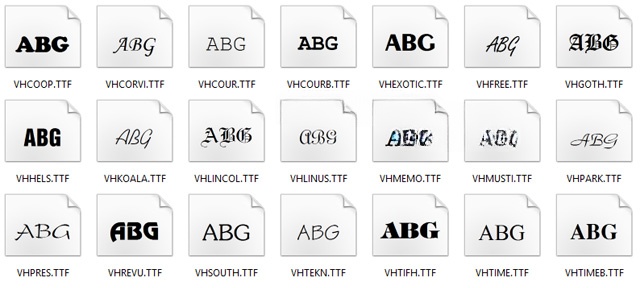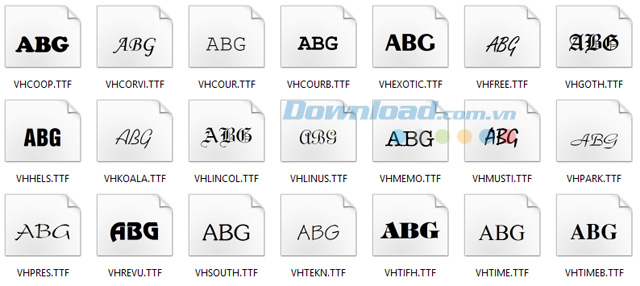
Bộ Font TCVN3 đầy đủFont hỗ trợ Tiếng Việt .Vn
Đây là danh sách bộ font TCVN3 đầy đủ (font tiêu chuẩn Việt Nam 3) hay có tên khác là font ABC bao gồm những font chữ thông dụng như .VNTime, .VNArial...
Bộ Font TCVN3 đầy đủ là font chữ tiếng Việt tiêu chuẩn Việt Nam phổ biến nhất hiện nay với với font chữ cơ bản như: .VNTime, .VNArial, vv. Bộ Font TCVN3 đầy đủ sẽ giúp bạn có thể nhập tiếng Việt khi soạn thảo văn bản, thiết kế, trò chuyện trên các ứng dụng chat và bộ font TCVN3 tương thích với bộ gõ tiếng Việt: Unikey, Vietkey, vv.
Một số font chữ họ TCVN3 trong bộ font TCVN3
Đặc điểm nổi bật của bộ font TCVN3
- Hỗ trợ Tiếng Việt đầy đủ (dấu và ký tự): Font TCVN3 được thiết kế với các mã hóa đặc biệt, giúp hiển thị đầy đủ và chính xác các ký tự tiếng Việt có dấu (sắc, huyền, hỏi, ngã, nặng) và các nguyên âm đặc biệt (.VnTime, .VnArial, v.v.).
- Đa dạng về kiểu chữ: Bộ font này thường bao gồm một hệ thống phong phú với hơn 100 kiểu chữ khác nhau, cho phép người dùng có nhiều lựa chọn về kiểu dáng để làm đẹp văn bản và thiết kế.
- Tương thích cao với bộ gõ: TCVN3 có khả năng tương thích tốt với các bộ gõ tiếng Việt nổi tiếng như Unikey và Vietkey, giúp việc soạn thảo văn bản tiếng Việt trở nên dễ dàng và nhanh chóng (thao tác chọn bảng mã TCVN3 trong Unikey chỉ bằng một cú nhấp chuột).
- Quan trọng cho tài liệu cũ: Rất nhiều tài liệu, văn bản, và sách giáo khoa được soạn thảo từ nhiều năm trước vẫn sử dụng bảng mã TCVN3. Việc cài đặt bộ font này là rất cần thiết để đọc được nội dung của các tài liệu "cũ" này mà không bị lỗi font nghiêm trọng.
Sử dụng TCVN3 sẽ mang lại cho bạn những cảm xúc rất đặc biệt, vì cách soạn thảo sẽ không giống như khi bạn gõ chữ với Unicode. Gõ "lò dùng sóng" sẽ thành "lũ dựng súng", "lè nhè" → "lố nhố", "lâng bâng" → "lõng bõng", "tê mê" → "tờ mờ". Vì là tiêu chuẩn cũ, nên ta thường bắt gặp chuẩn này trong những tài liệu tương đối "cổ". Dù hiện tại, ít người sử dụng chuẩn này, nhưng vẫn sẽ cần đến nó để đọc được các tài liệu hoặc sử dụng trong những yêu cầu đặc biệt.
Bên cạnh đó, với tính năng tương thích cao với nhiều phần mềm và hệ điều hành cũ, đặc biệt là các ứng dụng văn phòng như Microsoft Word, Excel hay các phần mềm thiết kế cơ bản. Khi sử dụng bảng mã riêng theo tiêu chuẩn Việt Nam, TCVN3 giúp hiển thị đầy đủ các ký tự tiếng Việt có dấu mà không bị lỗi font khi mở trên các máy tính khác sử dụng cùng chuẩn. Đồng thời, bộ font này cũng dễ dàng tích hợp vào các tài liệu, hệ thống in ấn truyền thống hoặc các phần mềm quản lý văn bản cũ, đảm bảo tính ổn định và đồng nhất về hiển thị văn bản. Tuy nhiên, vì sử dụng bảng mã TCVN3, khi làm việc với các hệ thống hiện đại hoặc web, người dùng cần lưu ý chuyển đổi sang Unicode để tránh lỗi hiển thị.